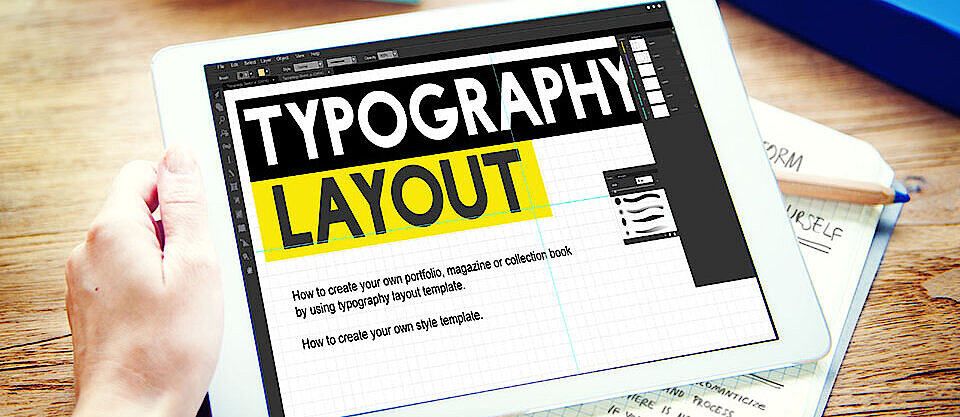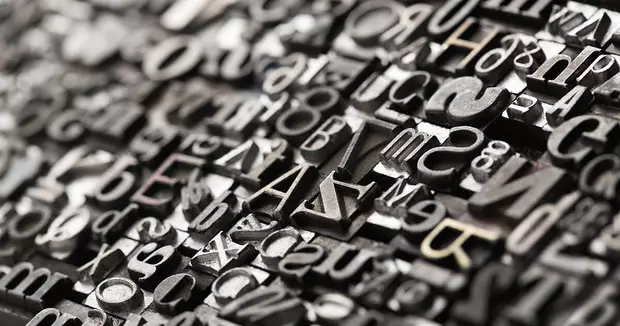
Comment la typographie est-elle utilisée aujourd’hui dans le design responsive ?
L’utilisation adéquate des polices de caractères joue un rôle majeur en design Web. Cela vaut également pour le responsive design, où la typographie influence fortement la perception d’un site Web.
Qu’est-ce que la typographie et comment se définit-elle aujourd’hui ?
À l’origine, la typographie désignait l’art d’imprimer des textes avec des caractères mobiles. Historiquement, le terme est étroitement lié au développement de l’écriture et à sa reproductibilité technique grâce à la presse d’imprimerie. Aujourd’hui, la notion est beaucoup plus large : la typographie englobe la conception des caractères et leur utilisation au sens le plus large. Cela comprend aussi la typographie numérique, telle qu’elle est employée sur les sites Web ou dans les programmes informatiques.
On distingue la microtypographie et la macrotypographie :
- Microtypographie : conception de la police elle-même ainsi que des espacements entre les signes et les mots
- Macrotypographie : ensemble des caractéristiques de mise en forme d’une page de texte imprimée ou numérique, y compris le format de page, la justification, la taille des caractères, les interlignes, le nombre et la largeur des lignes ainsi que le placement des autres éléments graphiques (par ex. images).
Comment la typographie est-elle utilisée sur Internet ?
Le terme « font » désigne un jeu de caractères numérique, c’est-à-dire une police spécifique utilisée sur ordinateur. La mise en forme des caractères dans les documents numériques et sur le Web est appelée typographie Web. Elle s’inspire de la typographie classique : la lisibilité dépend notamment de la taille de la police, de la longueur des lignes et de l’interligne. Pour les polices destinées au Web, il faut de plus tenir compte des formats de fichiers et du rendu dans le navigateur.
L’utilisation des polices sur le Web a fortement évolué. Autrefois, l’affichage était limité, car seules quelques polices comme Times New Roman ou Arial étaient considérées comme universellement compatibles et installées sur la plupart des systèmes. Aujourd’hui, les sites Web utilisent des polices variées sous forme de Webfonts. Les Webfonts sont des polices chargées depuis le Web via le CSS lors du chargement d’une page. Qu’elles soient locales ou Web, les polices modernes sont principalement des polices vectorielles, qui restent nettes à toutes les tailles. Les formats les plus courants sont TrueType (TTF), OpenType (OTF) et Web Open Font Format (WOFF2).
Que sont les variable fonts ?
Une évolution de la spécification OpenType est ce que l’on appelle les variable fonts. Il s’agit de polices qui regroupent plusieurs variantes, comme différentes graisses (poids), largeurs, inclinaisons ou autres caractéristiques typographiques, dans un seul fichier de police. Contrairement aux polices classiques, où chaque variante est chargée sous forme de fichier séparé, les variable fonts peuvent être ajustées de manière continue et flexible.
Cette technique permet d’adapter la typographie à différentes tailles d’écran, résolutions ou exigences de mise en page, sans passer d’une variante figée à une autre. Elle offre des avantages particuliers en responsive design : les graisses et tailles de police peuvent être ajustées de façon fluide, ce qui permet une intégration harmonieuse sur différents formats d’affichage. En parallèle, les sites Web bénéficient d’un nombre réduit de fichiers de polices, ce qui peut améliorer les temps de chargement et les performances globales.
Qu’est-ce qui caractérise la typographie en responsive design ?
La typographie Web a fortement évolué, mais le responsive design pose de nouveaux défis aux concepteurs Web. Le responsive design est une technique de design Web dans laquelle l’affichage d’une page Web s’adapte automatiquement à l’appareil utilisé et à la taille de l’écran. L’adaptation de tous les contenus à la taille d’écran concerne également la typographie : elle doit s’intégrer de manière cohérente dans chaque contexte d’affichage. Cela signifie que le rendu typographique doit être adaptable.
La taille de la police et les retours à la ligne s’ajustent idéalement à chaque format. Les fonctionnalités CSS permettent une typographie fluide, dans laquelle les tailles de police s’adaptent en continu à la zone d’affichage (viewport). Avec des fonctions comme clamp(), il est possible de définir des valeurs minimale, idéale et maximale pour le corps du texte, afin d’éviter des textes trop petits ou trop grands.
Plusieurs facteurs doivent être pris en compte en typographie Web :
- La taille de la police doit être adaptée à la taille de l’écran, mais aussi à la distance de lecture (plus courte sur mobile que sur desktop).
- Elle dépend également de la résolution de l’écran.
- L’interligne doit être adapté au format d’affichage et à la longueur des lignes.
- La mise en page doit prévoir des zones de respiration typographique, ce qui améliore la lisibilité.
Grâce aux polices vectorielles, la lisibilité est conservée sur tous les formats d’écran. Pour éviter de dépendre des polices préinstallées, il est possible d’intégrer des polices via CSS.
En plus de l’adaptation aux tailles d’écran, les techniques de mise en page évoluent. Les CSS Container Queries permettent d’adapter la typographie non plus uniquement au viewport, mais aussi à la taille de chaque composant. Les éléments peuvent ainsi réagir individuellement à l’espace disponible, ce qui permet une typographie encore plus précise dans des mises en page modulaires.